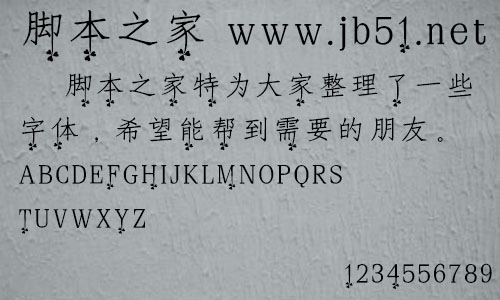
義啟三葉草物語體是由義啟字庫開發(fā)的一款中文藝術(shù)字體,這款字體的下方有四葉草的標(biāo)記,看上去煞是可愛,適合應(yīng)用于藝術(shù)設(shè)計(jì)、平面宣傳設(shè)計(jì)、網(wǎng)頁設(shè)計(jì),書法字帖等領(lǐng)域,需要的朋友可以前來本站下載。